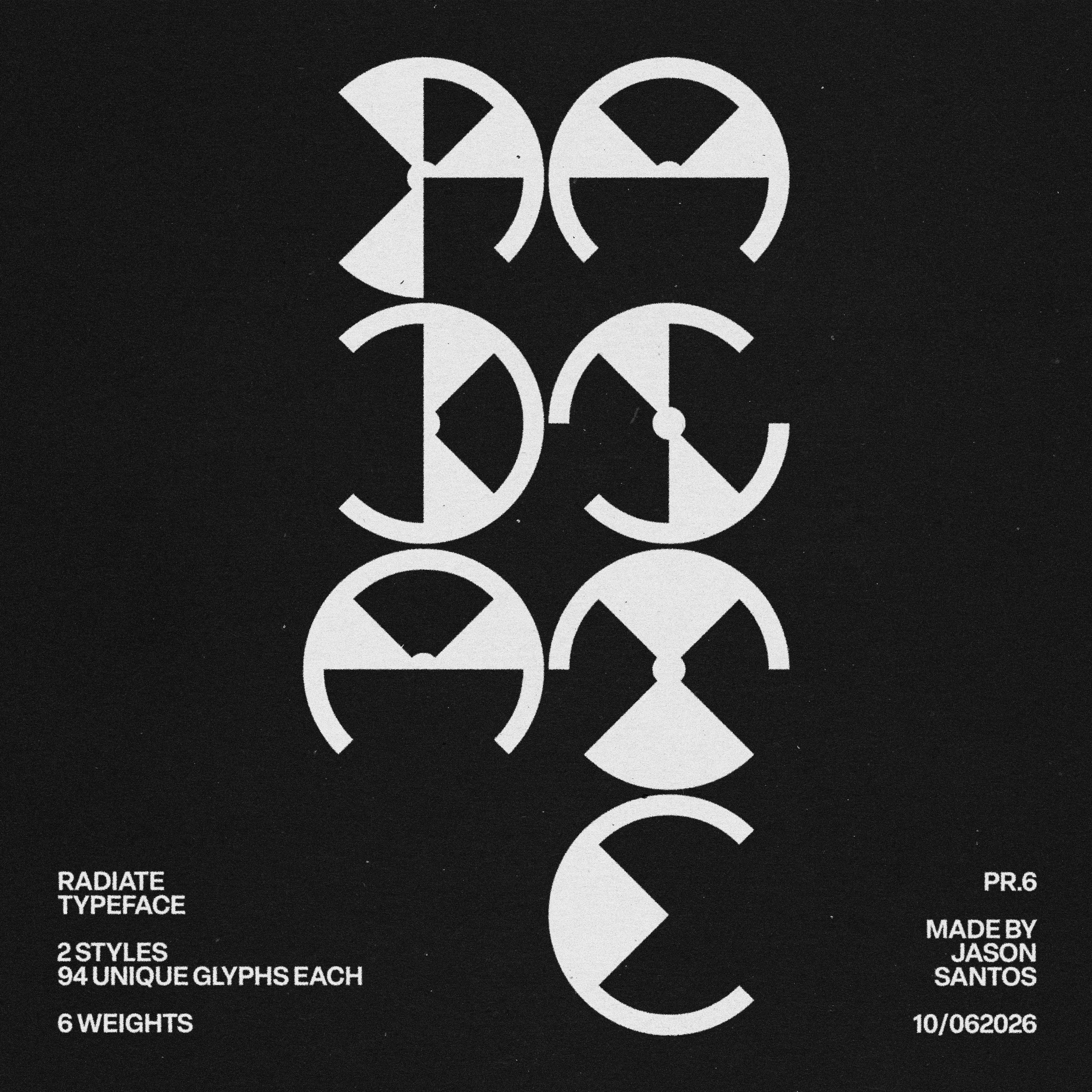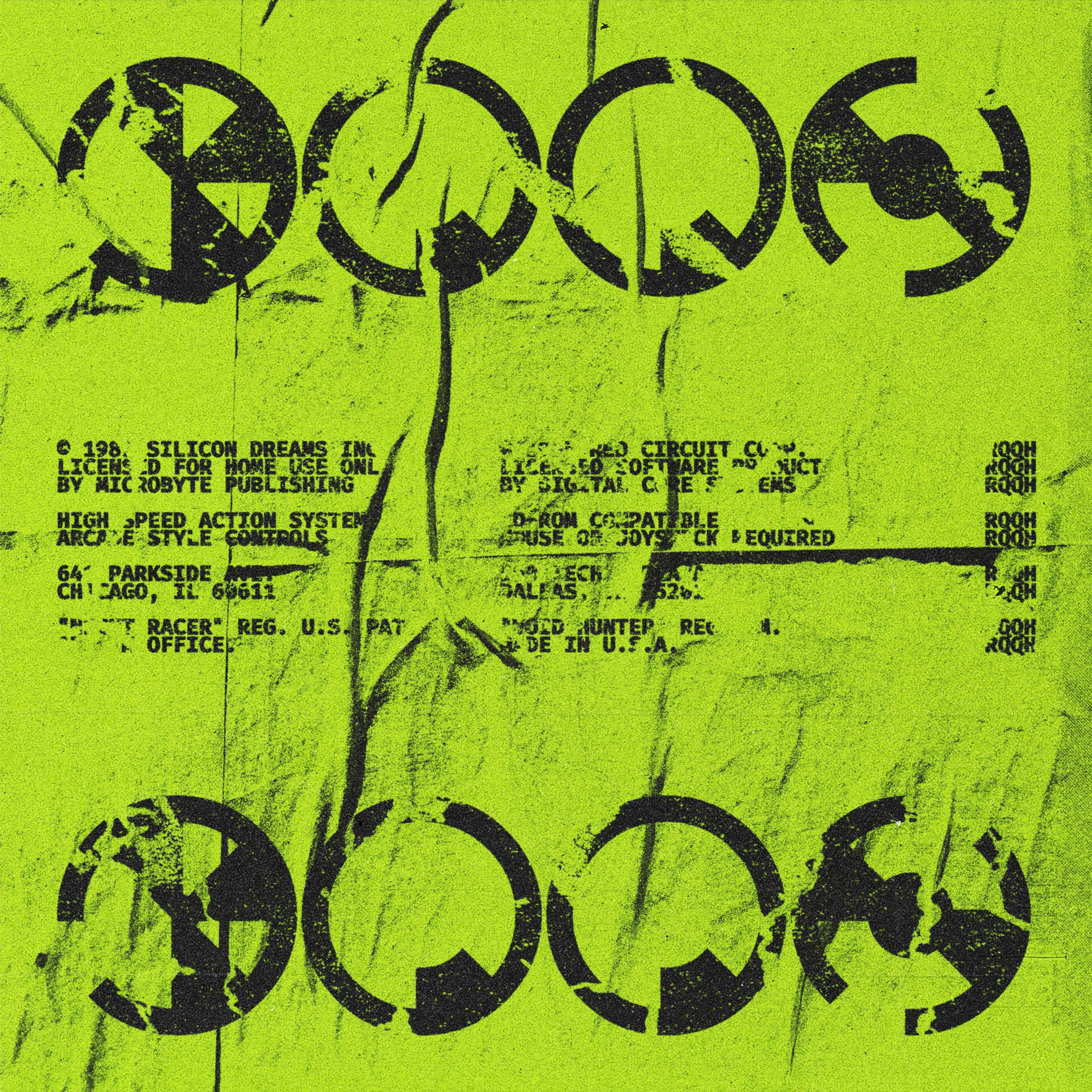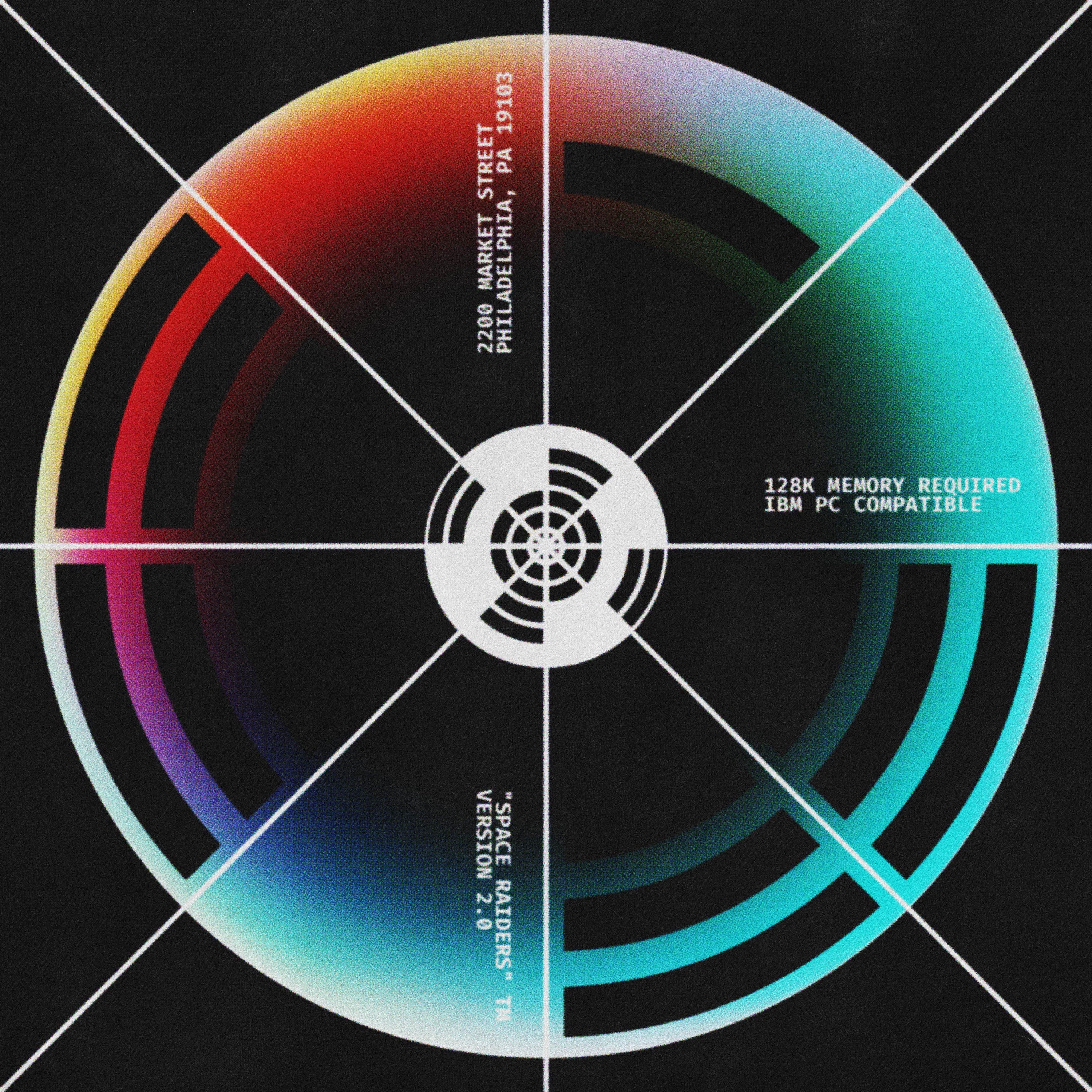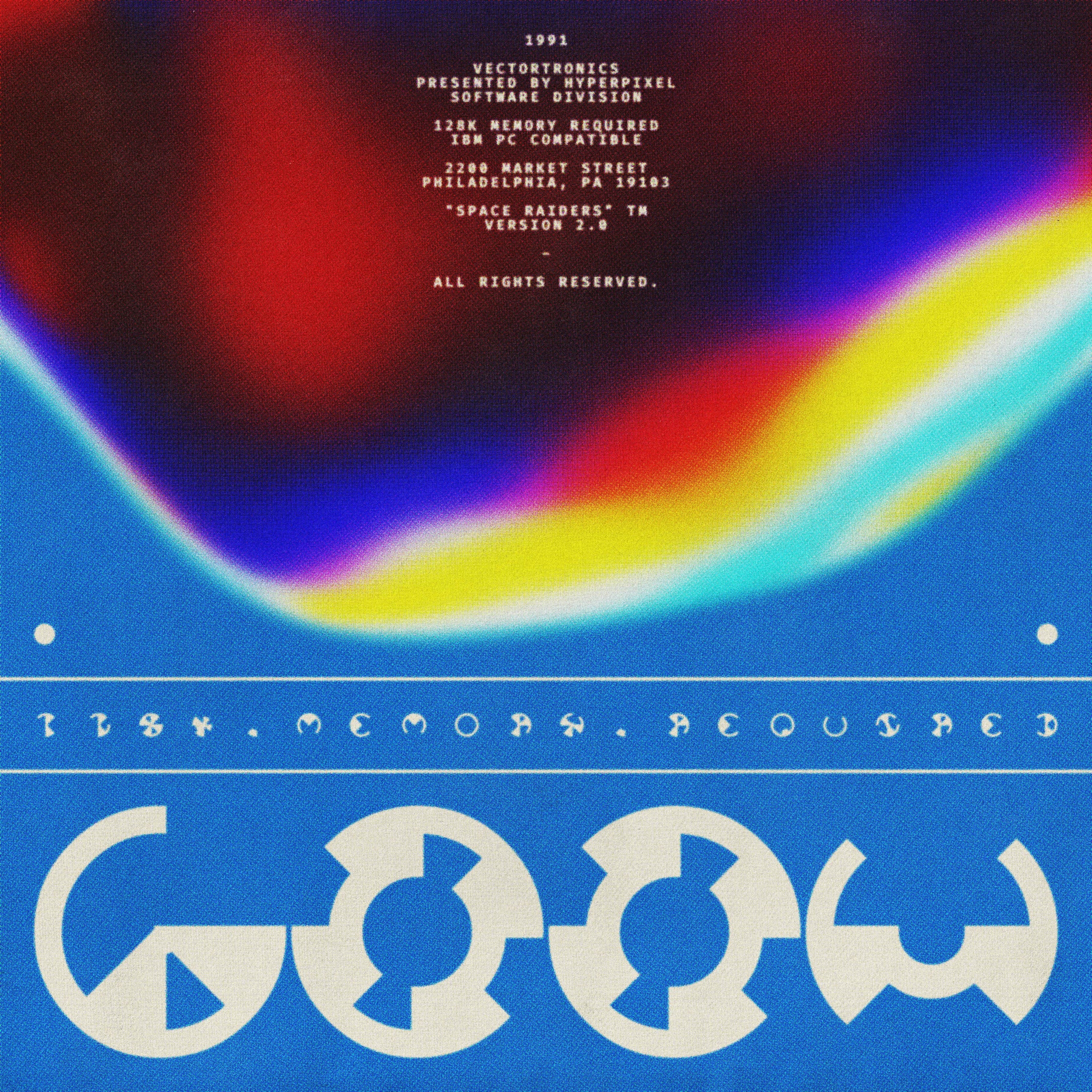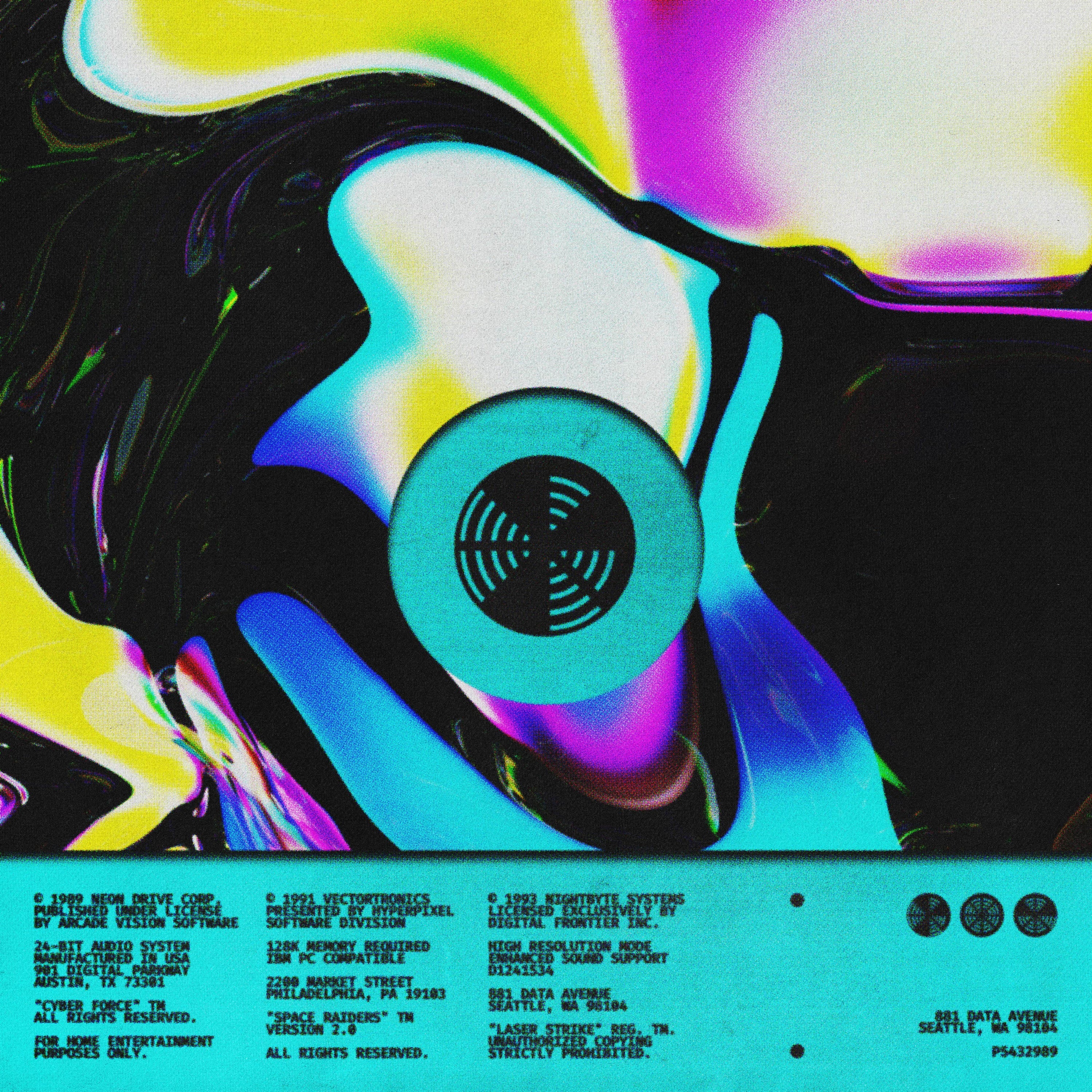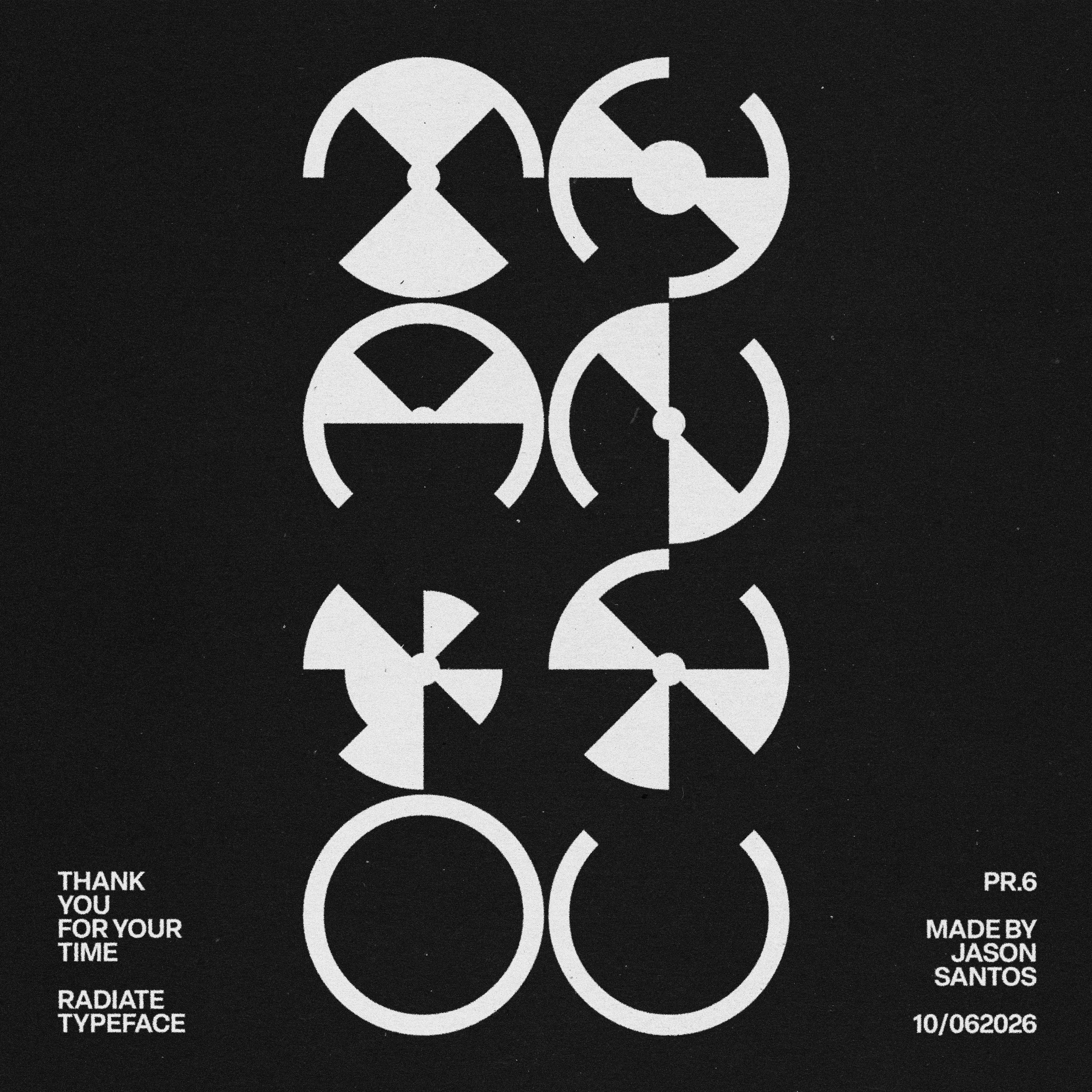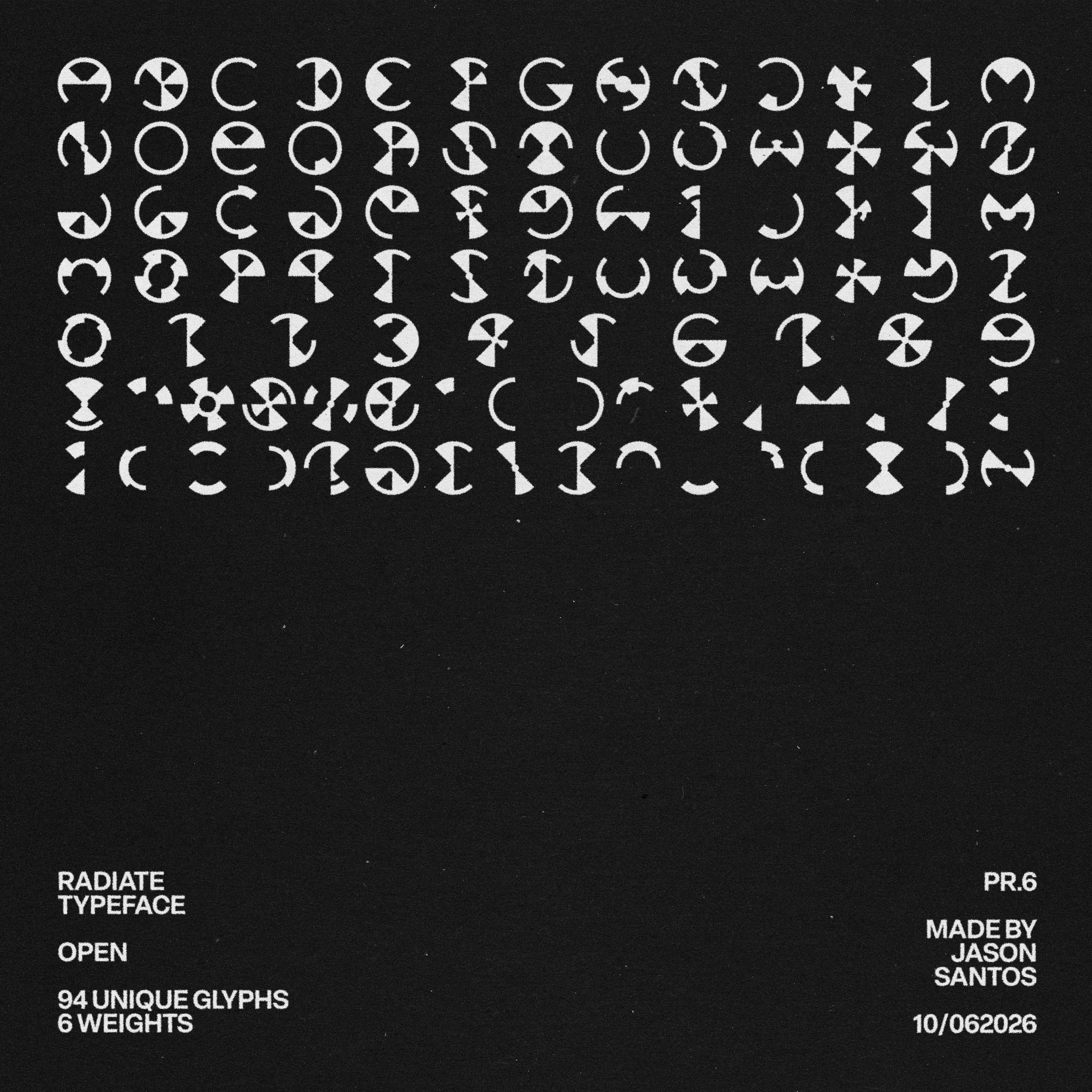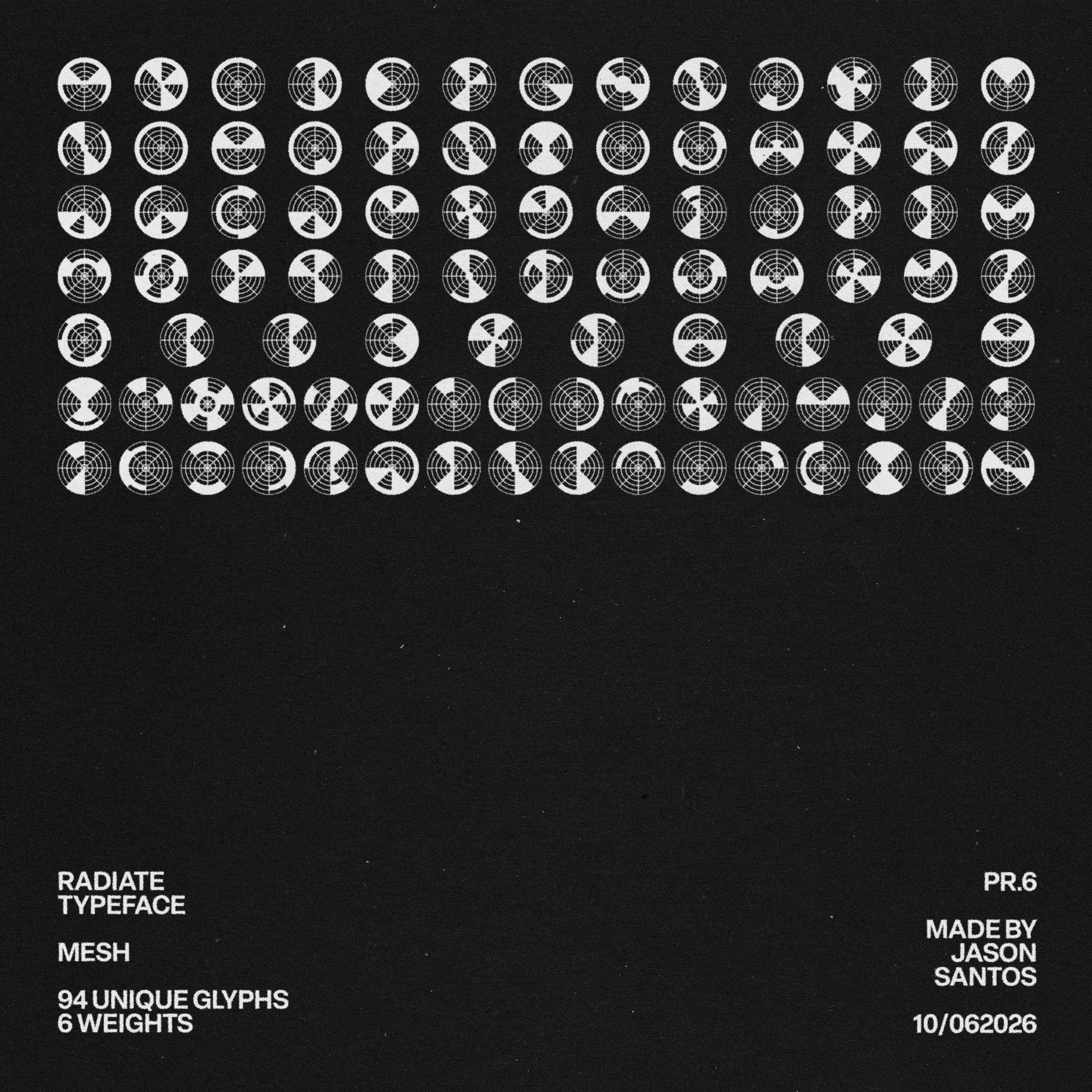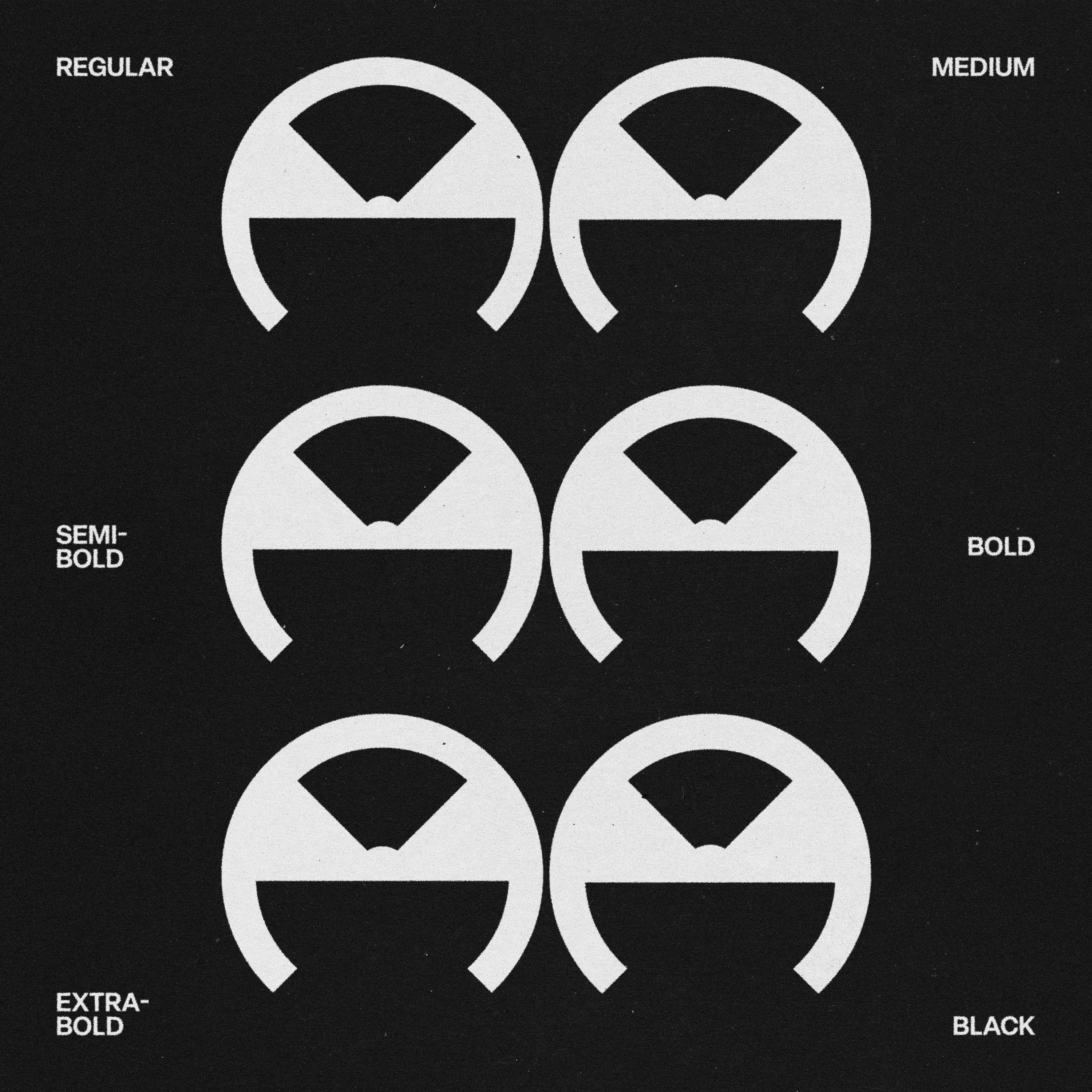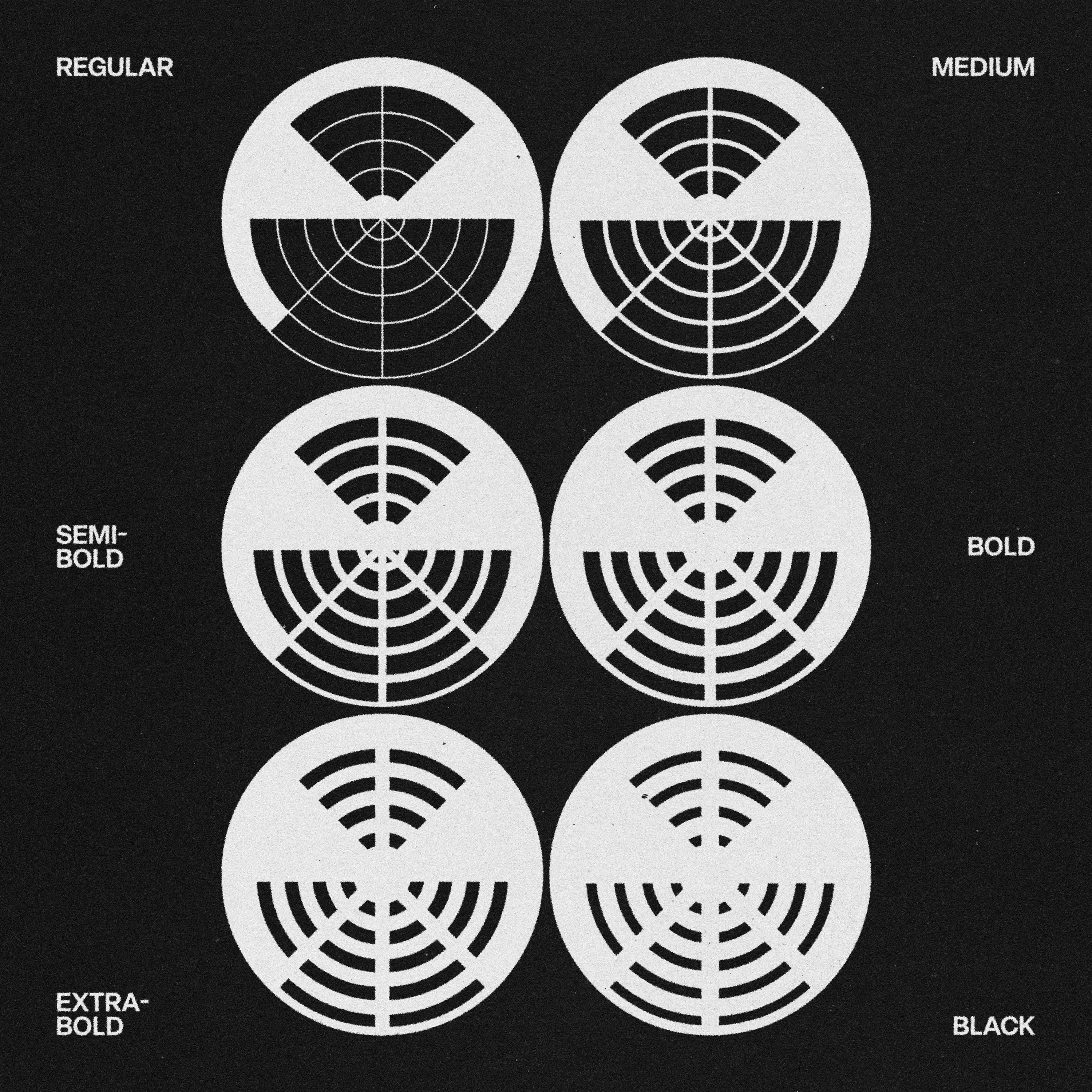
Tipografía Radiate
Radiate es una tipografía experimental de exhibición construida en torno al movimiento fluido, la rotación abstracta y las estructuras de letras poco convencionales. Sus formas únicas crean una sensación de movimiento, transformando la tipografía en un objeto visual en lugar de un simple texto.
Disponible en dos estilos distintos — Open y Mesh — Radiate explora el contraste entre la construcción geométrica limpia y las estructuras más fragmentadas y orgánicas. Las múltiples opciones de peso proporcionan flexibilidad, permitiendo a los diseñadores crear desde maquetaciones experimentales refinadas hasta declaraciones visuales audaces.
Perfecta para branding vanguardista, carteles, identidades de moda, portadas de álbumes, diseño editorial, empaques y experimentos gráficos contemporáneos, Radiate aporta una personalidad futurista y artística a cualquier proyecto.
Características
• 94 Glifos
• 12 Estilos (Open Regular, Open Medium, Open Semi-Bold, Open Extra-Bold, Open Black, Mesh Regular, Mesh Medium, Mesh Semi-Bold, Mesh Extra-Bold, Mesh Black)
• Minúsculas
• Mayúsculas
• Números
• Puntuación
• Símbolos
• Matemáticas